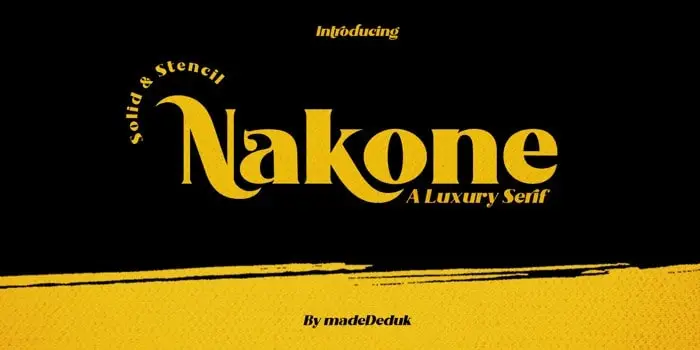
Nakone Serif Font
A Nakone Serif Font é uma elegante tipografia serif que combina sofisticação com modernidade. Desenvolvida pelo criador de fontes madeDeduk na plataforma 99designs, esta tipografia exibe um forte estilo luxuoso e elegante, contendo tanto versões de texto sólido quanto stencil. Suas alternativas estilizadas oferecem infinitas possibilidades para projetos variados, desde editoriais e blogs até logomarcas e design web. Ideal para revistas, editoriais, sites e qualquer projeto que busque um toque sofisticado e elegante. Uma fonte irresistível para aqueles buscando uma maneira única de dar vida a suas ideias visuais.